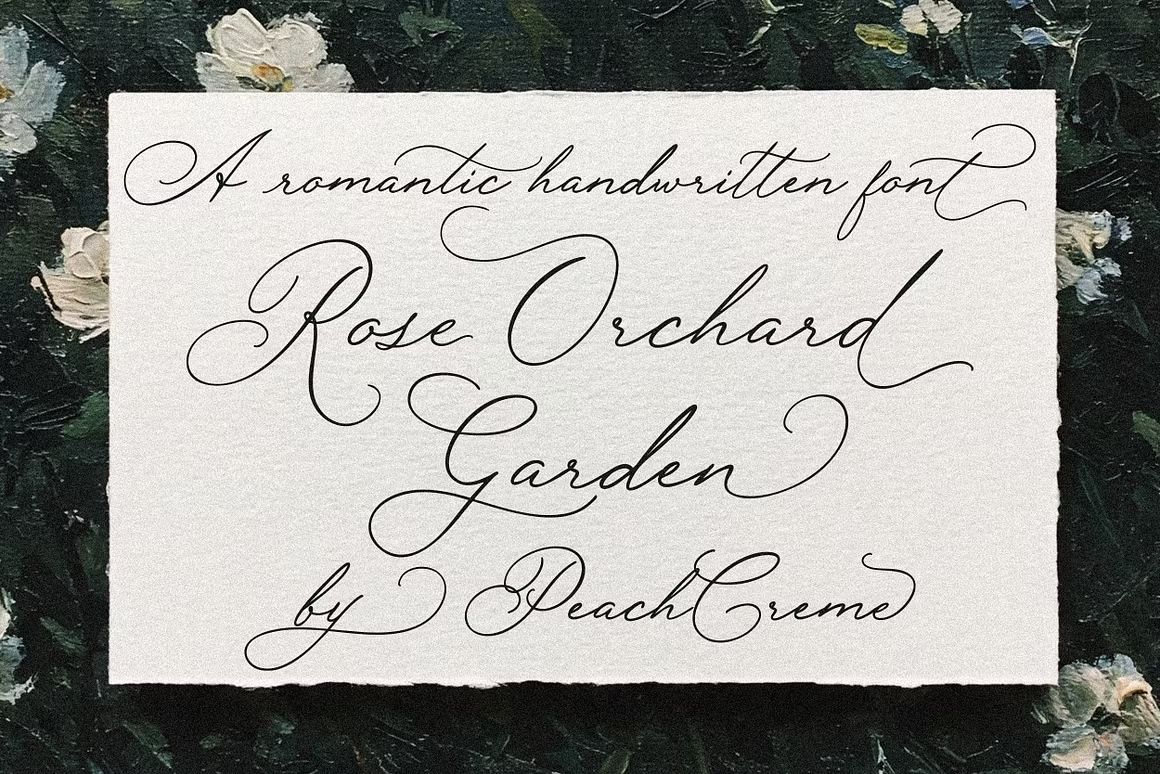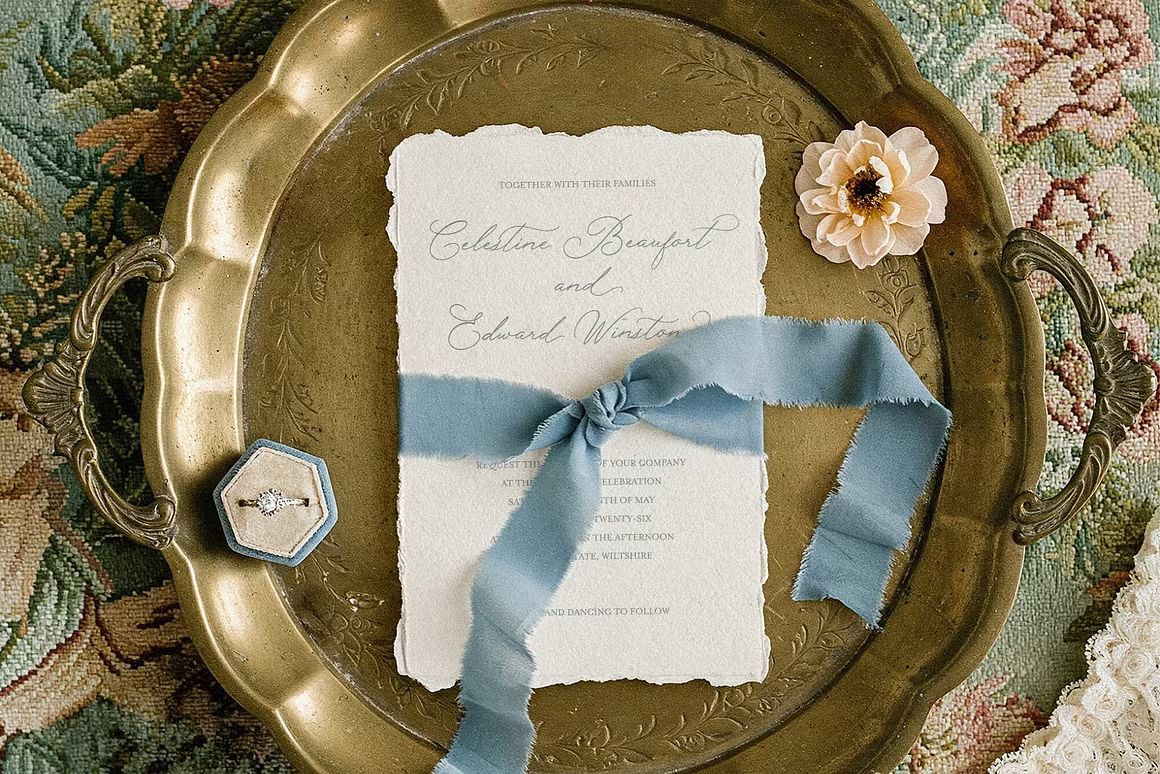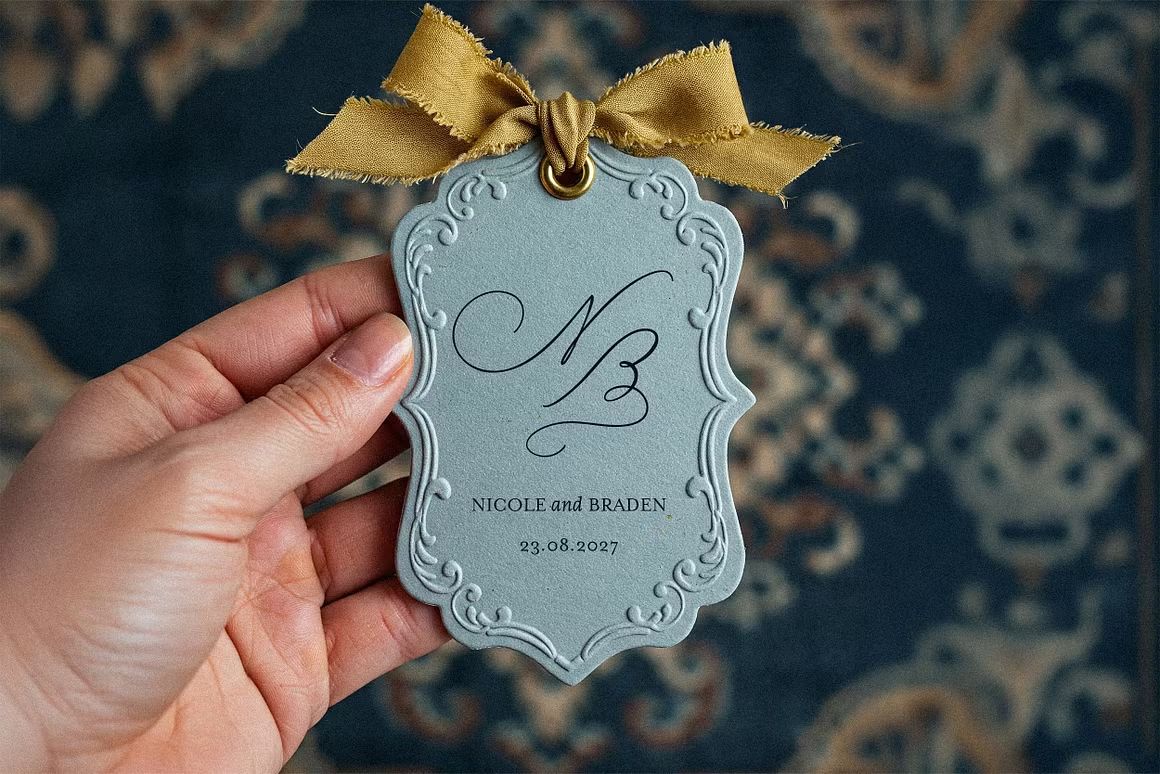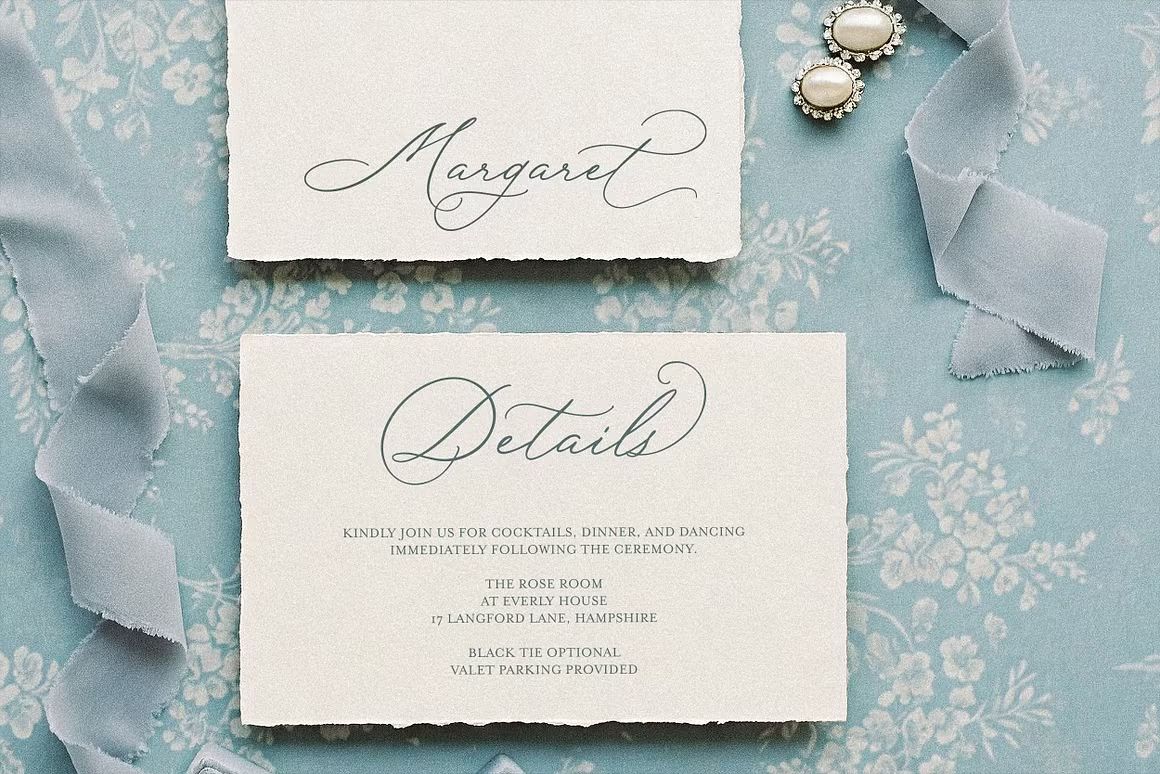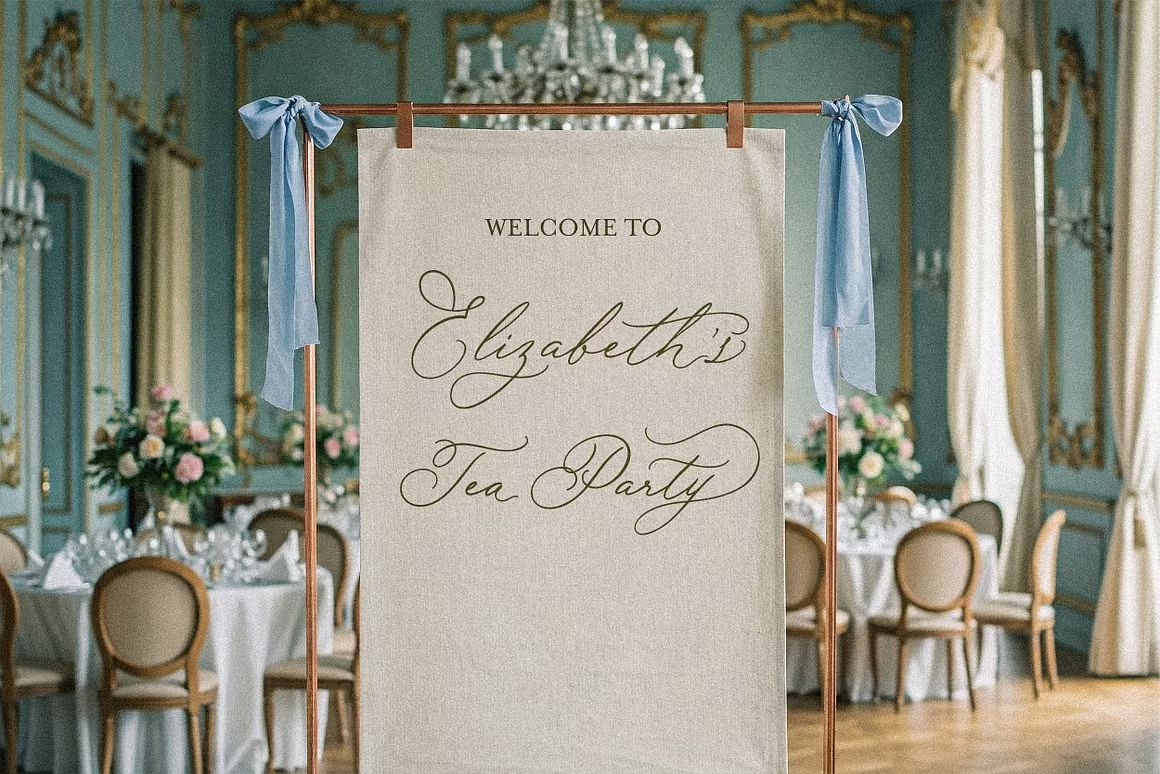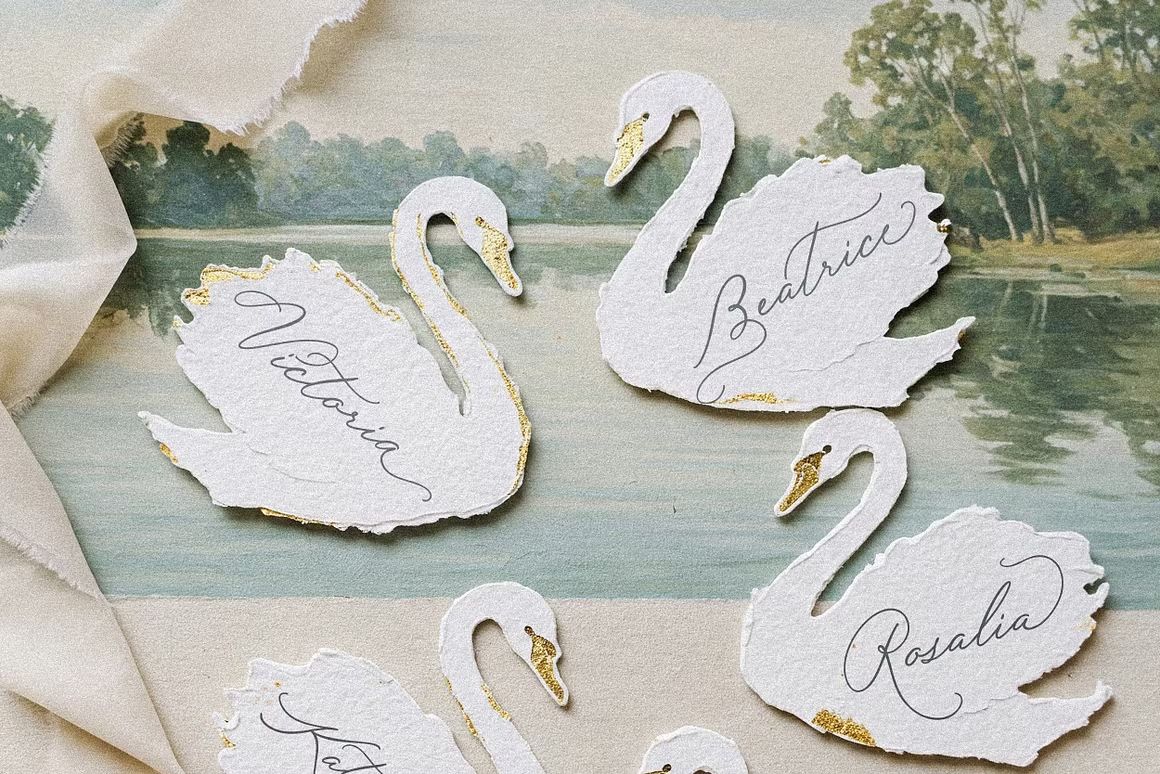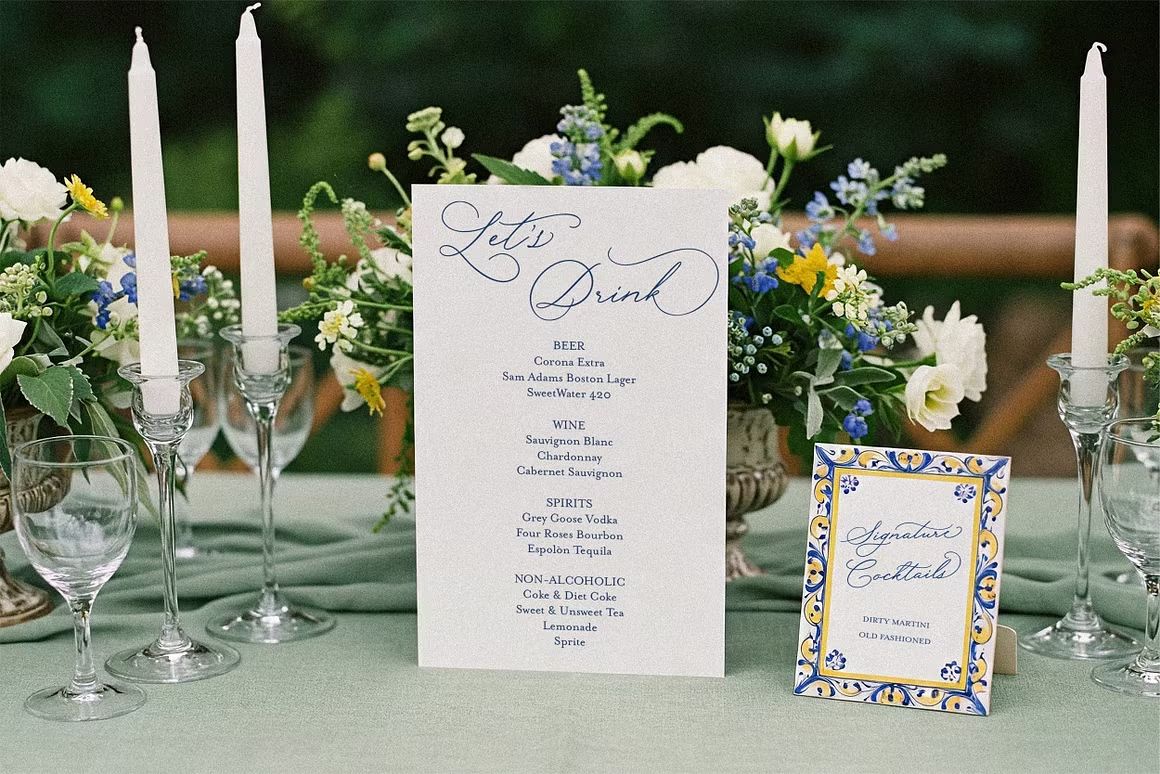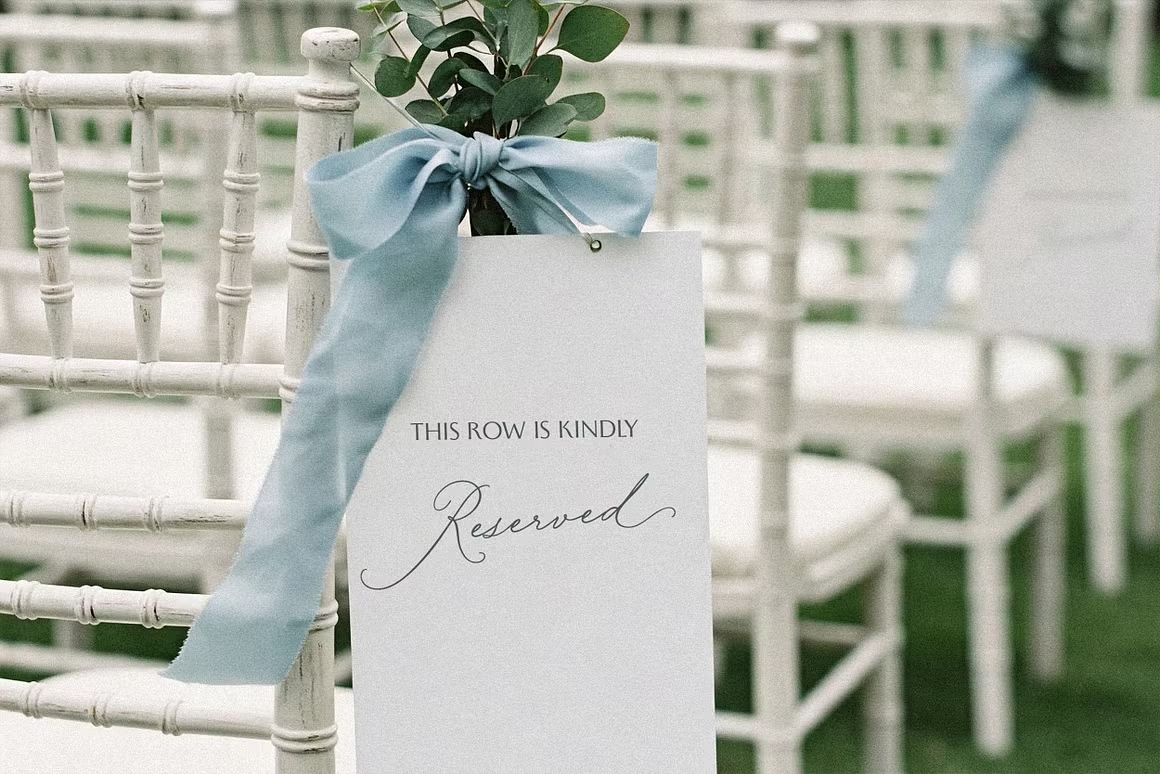
Rose Orchard Garden – Script Font
Rose Orchard Garden adalah font script bergaya elegan dan feminin, sempurna untuk desain pernikahan, undangan, branding, dan proyek kreatif yang membutuhkan sentuhan manis dan anggun.
Rose Orchard Garden adalah font script yang anggun dan feminin dengan goresan tangan yang halus dan romantis. Cocok digunakan untuk undangan pernikahan, branding, logo, kemasan produk, dan berbagai proyek desain yang ingin tampil elegan dan penuh keindahan. Font ini menghadirkan nuansa hangat dan personal yang mempercantik setiap karya visual Anda.
• Gaya script elegan dengan tampilan tulisan tangan
• Cocok untuk wedding, branding, logo, dan packaging